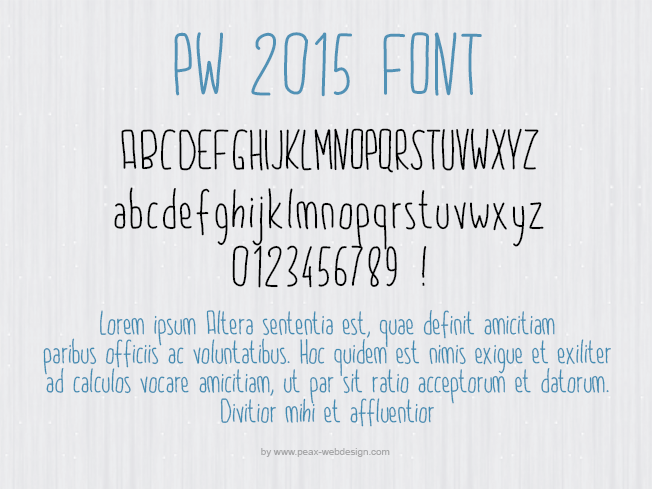
PW 2015, police manuscrite au format .ttf.
PW 2015, conçue bien évidemment en ce début d'année 2015 est une police de caractères manuscrite, volontairement maladroite et presque enfantine , ce qui lui confère un charme particulier et un aspect convivial. Elle est adaptée autant à la lecture en petite taille qu'aux gros titrages, les utilisations sont variées. Pour un usage commercial, merci de me contacter.